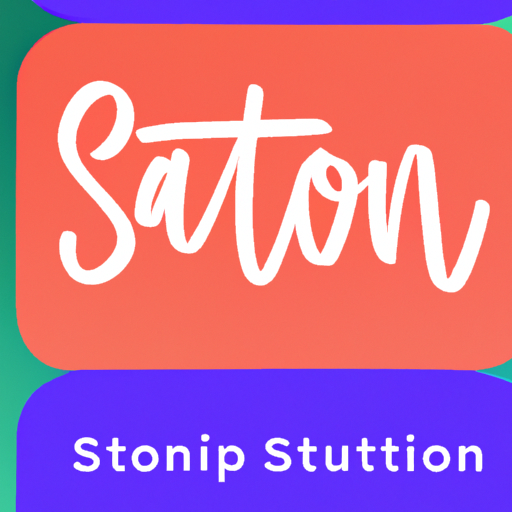
מדריך זה מספק סקירה מקיפה של יצירת גופנים, במטרה להדריך אותך בתהליך מניסוח עיצובים ראשוניים ועד ליישום הסופי של הגופן המותאם אישית שלך. אנו מכסים הן את ההיבטים היצירתיים, כגון המשגה ושרטוט העיצובים שלך, כמו גם את ההיבטים הטכניים, כגון שימוש בתוכנה ליצירת גופנים ובדיקת הגופנים שלך.
הבנת היסודות: מה מייצר גופן?
גופן הוא ייצוג חזותי של תוכן טקסטואלי, המורכב מקבוצה של תווים עם אלמנטים עיצוביים עקביים. זהו היבט מכריע בעיצוב גרפי ועיצוב אתרים, מכיוון שהוא עוזר להעביר את המסר המיועד והאסתטיקה של פיסת טקסט. גופנים יכולים לנוע בין פשוטים ומינימליסטיים למורכבים ודקורטיביים, ולכל גופן יש את הסגנון והאישיות הייחודיים לו.
בעת יצירת גופן, חיוני להבין את המרכיבים הבסיסיים המרכיבים את הגופן. מרכיבי המפתח כוללים את צורות האותיות, שהן הצורות האישיות של כל תו, כגון הקימורים, הקווים והזוויות. המרווח בין התווים, המכונה קרנינג, חשוב גם בקביעת הקריאה והזרימה הכוללת של הטקסט. בנוסף, וריאציות הגודל, המשקל והסגנון, כגון מודגש, נטוי או קו תחתון, תורמים לרבגוניות ולכושר הביטוי של גופן.
כדי ליצור גופן, יש לשקול גם את המטרה המיועדת וקהל היעד. גופנים שונים מתאימים להקשרים שונים, כגון חומרי הדפסה, אתרי אינטרנט או שילוט. לדוגמה, גופן בעל קריאות וקריאות גבוהה עשוי להתאים יותר לגוף הטקסט, בעוד שגופן דקורטיבי ומקושט עשוי להתאים יותר לכותרות או לוגואים.
יתר על כן, חשוב שתהיה הבנה מוצקה של עקרונות טיפוגרפיה ועקרונות עיצוב. זה כולל ידע של היררכיה, איזון וניגודיות, כמו גם הבנה של האופן שבו גופים שונים מקיימים אינטראקציה ומשלימים זה את זה. גופן מעוצב היטב צריך להיות אסתטי, קוהרנטי ופונקציונלי.
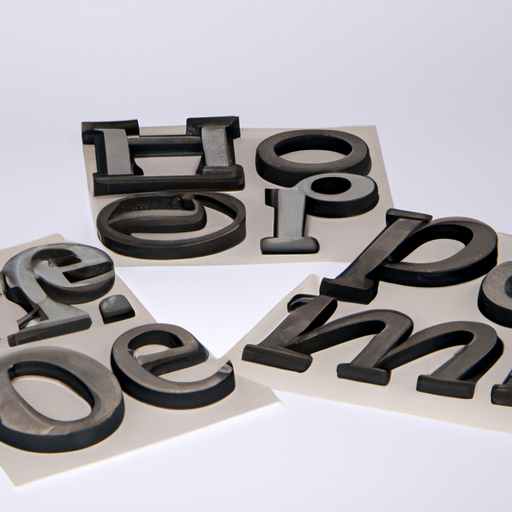
תמונה המציגה רכיבים שונים של גופן
מציאת השראה: איך נוכל ליצור משהו ייחודי?
השראה היא גורם מפתח ביצירת גופן ייחודי. הניצוץ הוא שמצית את היצירתיות ומניע את תהליך העיצוב. כדי למצוא השראה, אפשר לחקור מקורות וטכניקות שונות.
ראשית, לימוד גופנים קיימים יכול לספק תובנות ורעיונות בעלי ערך. ניתוח גופים שונים, ההקשר ההיסטורי שלהם והרגשות שהם מעוררים יכולים לעורר כיווני עיצוב חדשים. בנוסף, בחינת עבודתם של טיפוגרפים וקליגרפים ידועים יכולה להציע השראה והדרכה.
שנית, חקר תחומי אמנות חזותיים ועיצוב שונים יכול להרחיב אופקים יצירתיים. שאיבת השראה מתנועות אמנות, כמו אקספרסיוניזם מופשט או באוהאוס, יכולה להחדיר אלמנטים ייחודיים לעיצוב גופן. באופן דומה, הסתכלות על אדריכלות, אופנה או טבע יכולה להציע נקודות מבט ומושגים רעננים.
יתרה מכך, עיסוק במחקר תרבותי יכול להוביל ליצירת גופנים מגוונים ומכילים מבחינה תרבותית. חקירת סקריפטים, שפות ומערכות כתיבה שונות יכולה להביא לגופנים שפונים לקהל עולמי ומקדמים את ההכללה.
יתר על כן, התנסות בכלים וטכניקות שונות יכולה להוביל לתוצאות בלתי צפויות וחדשניות. ניסיון מכשירי ציור שונים, כגון עטי מברשת או טאבלטים דיגיטליים, יכול ליצור טקסטורות וצורות ברורות. חקר שיטות לא שגרתיות, כמו כיתוב יד או קולאז', יכול גם לייצר עיצובי גופנים ייחודיים ולא שגרתיים.
"הגבול היחיד למימוש המחר שלנו יהיה הספקות שלנו של היום". – עיצוב סקיצות הגופן שלך
עיצוב סקיצות גופנים הוא שלב חיוני בתהליך יצירת הגופן. זה המקום שבו רעיונות מתגבשים ומתחילים להתממש. כפי שהציטוט מרמז, ספקות יכולים לעכב את ההתקדמות שלנו, ולכן חיוני לגשת לשרטוט בביטחון ובראש פתוח.
כאשר מתחילים את תהליך השרטוט, כדאי להקפיד על חזון או קונספט ברורים. זה יכול להתבסס על ההשראה שנאספה או על המטרה הספציפית של הגופן. קיום כיוון מבטיח שהסקיצות יתאימו לתוצאה הרצויה.
במהלך השרטוט, חשוב לחקור וריאציות ואיטרציות שונות. זה מאפשר ניסויים וגילוי אלמנטים ייחודיים שיכולים לייחד את הגופן. ניסיון של צורות אותיות שונות, רוחב קו ופרופורציות יכול להוביל לתוצאות בלתי צפויות ומרגשות.
בזמן הרישום, כדאי גם לשקול את המעשיות והקריאות של הגופן. גופנים צריכים להיות פונקציונליים וקראים בהקשרים וגדלים שונים. לכן, הערכת הסקיצות לבהירות ועקביות היא חיונית כדי להבטיח גופן מעוצב ושמיש.
חשוב לא להתייאש מפגמים או ספקות ראשוניים. שרטוט הוא תהליך של עידון ואיטרציה, ורעיונות מתפתחים עם הזמן. אימוץ המסע היצירתי ופתיחות למשוב וביקורת יכולים לעזור להתגבר על ספקות ולדחוף את העיצוב קדימה.
ספר סקיצות עם סקיצות גופנים ראשוניות
תוכנה ליצירת גופנים: איזו מהן מתאימה לך?
כשזה מגיע ליצירת גופנים, בחירת תוכנה נכונה ליצירת גופנים היא חיונית. קיימות מספר אפשרויות זמינות, כל אחת עם תכונות ויכולות משלה. להלן שלוש תוכנות פופולריות ליצירת גופנים שכדאי לקחת בחשבון:
- 1. Adobe Illustrator:
Adobe Illustrator היא תוכנת עיצוב רבת עוצמה מבוססת וקטור בשימוש נרחב על ידי מעצבים. הוא מציע מגוון כלים ותכונות שהופכים אותו למתאים ליצירת גופנים. עם השליטה המדויקת שלו על צורות ועקומות, מעצבים יכולים ליצור צורות אותיות נקיות ומוגדרות היטב. Illustrator מספקת גם אפשרויות להוספת אפקטים מיוחדים, התאמת ליבה וייצוא גופנים בפורמטים שונים של קבצים. - 2. גליפים:
Glyphs היא תוכנה ייעודית לעיצוב גופנים שנבנתה במיוחד ליצירת גופנים. הוא מציע סט מקיף של כלים ותכונות המותאמות לצרכים של מעצבי גופנים. Glyphs מספק ממשק ידידותי למשתמש עם פקדים אינטואיטיביים לעריכת צורות אותיות, התאמת מרווחים וניהול מדדי גופנים. הוא כולל גם תכונות מתקדמות כמו תמיכה ב-OpenType, יצירת ליגטורות ואינטרפולציה אוטומטית ליצירת משפחות גופנים. - 3. FontLab:
FontLab היא תוכנה פופולרית נוספת ליצירת גופנים. הוא מציע מגוון רחב של כלים רבי עוצמה לעיצוב, חידוד והפקה של גופנים. FontLab מאפשר למעצבים לצייר ולערוך צורות אותיות בדייקנות, להתאים זוגות ליבה וליצור תכונות OpenType. הוא גם מספק תכונות כמו יצירת גופנים משתנים, החלפת גליפים ותאימות עם תוכנות עריכת גופנים אחרות.בחירת התוכנה הנכונה ליצירת גופנים תלויה בצרכים, בהעדפות וברמת המומחיות הספציפיים שלך. שקול גורמים כגון ממשק משתמש, כלים זמינים, קלות שימוש ותאימות למערכת ההפעלה שלך. בנוסף, חפש תוכנה שמציעה תמיכת לקוחות טובה ועדכונים שוטפים כדי להבטיח תהליך יצירת גופנים חלק ויעיל.
| 3. עיצוב ויצירת גופנים | השתמש בתוכנה ליצירת גופנים כדי לעצב וליצור את הגופנים שלך. | 2 שעות | 0 ₪ |
יצירת גופנים משלך היא תהליך מאתגר אך מתגמל המשלב יצירתיות, מיומנויות טכניות והבנה עמוקה של טיפוגרפיה. עם סבלנות ותרגול, אתה יכול ליצור גופים ייחודיים ואקספרסיביים שיכולים להשאיר השפעה מתמשכת על פרויקטי העיצוב שלך. זכור, כל גופן נהדר התחיל כרעיון פשוט, אז אל תפחד להתנסות ולתת ליצירתיות שלך לזרום.